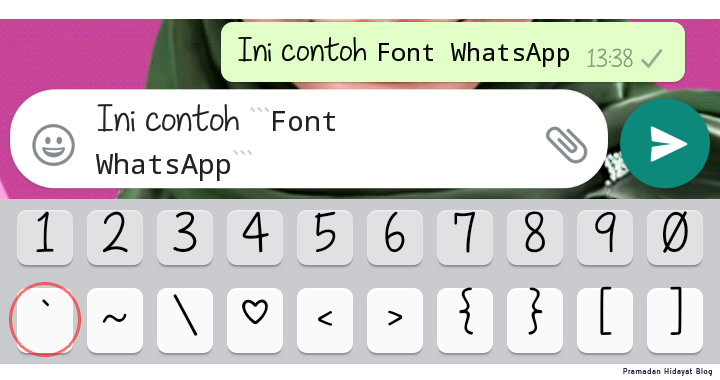
Что за «кодовый» шрифт в рекламных роликах и фильмах? | by Andrew Crites
Вы, наверное, видели такие вещи, как изображение статьи или вот это:
или это:
в фильмах, телешоу, рекламе и т. д.
Если вы не являетесь разработчиком программного обеспечения или мало что знаете о разработке программного обеспечения, вы, возможно, задаетесь вопросом: «Что это за кодовый шрифт
?» Или, может быть, вы не задавались вопросом — может быть, вы просто считаете само собой разумеющимся, что всем разработчикам нравится работать в какой-то таинственной среде, которая печатает только роботизированный шрифт так, как его могут понять компьютеры и компьютерные гении. На самом деле «кодовый шрифт» — это гораздо больше, чем вы думаете, и причины его использования имеют смысл.
Так что же это за шрифт?
Шрифт, обычно используемый для разработки программного обеспечения, называется моноширинным шрифтом. В этом шрифте каждый символ занимает одинаковое количество места. Сюда входят любые буквы и цифры, в том числе
i
и 1
, и даже пробелы, созданные с помощью пробела.
На самом деле не существует ни одного моноширинного шрифта. Доступно множество различных моноширинных шрифтов.
Courier и Courier new:
Courier, моноширинный шрифт, представленный в 1955 и используется пишущими машинкамиCourier NewFiracode, популярный современный шрифт для разработки программного обеспеченияДоступны всевозможные моноширинные шрифты. Это действительно зависит от предпочтений разработчика и от того, как он настроит свою машину в зависимости от того, как выглядят шрифты и цвета. Один общий фактор в моноширинных шрифтах заключается в том, что каждый символ занимает одинаковое количество места.
Зачем использовать моноширинный шрифт?
Моноширинный шрифт может показаться немного загадочным людям, которые с ним не знакомы. Если вы не разработчик и кто-то попросил вас сесть перед терминалом и начать программировать, вы можете подумать, что вы есть , чтобы написать свой код зеленым шрифтом на черном фоне в Courier New. На самом деле это не так, и любое современное терминальное приложение, с которым вы работаете, позволит вам выбрать любые цвета или шрифты, которые вы хотите.
Разработчики почти всегда используют моноширинный шрифт, потому что мы читаем код не так, как текст. Вы можете понять значение большого блока текста, бегло взглянув на части слов и на то, как они сочетаются друг с другом. На самом деле, msot poelpe может воспроизвести сетакны с фильтрами, перемешанными с фоном, так же сложно, как sirt и lsat звуки в основных точках.
Это не относится к коду. Код — это определенный набор инструкций, которые должны следовать точному синтаксису, чтобы их могли понять компьютеры. Даже один неуместный символ может помешать работе всей программы.
Неизвестная опция «watchc.» Отступы также особенно важны для разработчиков, потому что они позволяют нам увидеть, как «течет» наша программа. В некотором смысле код — это река, которая разветвляется на множество ответвлений или притоков. Когда вы запускаете программу, вы пускаете лодку вниз по реке и выбираете, какие ответвления выбрать. Например:
Это простая программа, которую вы можете прочитать следующим образом:
- Если заданное число
число
больше 5… - …и делится на 2, выведите «A!»
- … и это , а не , кратное 2, выведите «B!»
- Если задано число , а не больше 5, а равно больше 0, выведите «C!»
- Если ни одно из вышеперечисленных условий не было выполнено (т.е. число не больше 5 и число не больше 0 (т.е. число отрицательное)) выведите «D!»
Возможно, будет проще представить это в виде графика/дерева/реки, используя аналогию, приведенную выше:
Эта программа может показаться маленькой, бесполезной или тривиальной. Однако многие небольшие программы, подобные этой, выполняют небольшие вычисления, из которых формируются строительные блоки более полезных программ.
Разработчики программного обеспечения научились читать этот код ветвления довольно рано. Код не читается как поэзия или проза. Вместо этого вы научитесь интерпретировать фрагменты кода как отдельные символы, которые вы сможете распознать по форме. , если (число > 5)
имеет тот же визуальный эффект, что и…
Более того, отступ важен. Возвращаясь к приведенному выше примеру:
Вы можете видеть, как код разветвляется по тому, насколько он отступлен. Вы можете видеть, что печатает "A!"
отступает дальше, чем печатать "C!"
. Это быстрый визуальный индикатор того, что печатает "A!"
зависит от большего количества ветвей, чем выведите "C!"
Сравните это с кодом без отступа:
Не слишком полезно для старых книг. Это дало мне четыре разных ответа на четыре разных слова с одной страницы книги, из книги 1991 года. Также выводит список возможностей, а не сводит их к одному. Может быть лучше для новых компьютерных шрифтов.